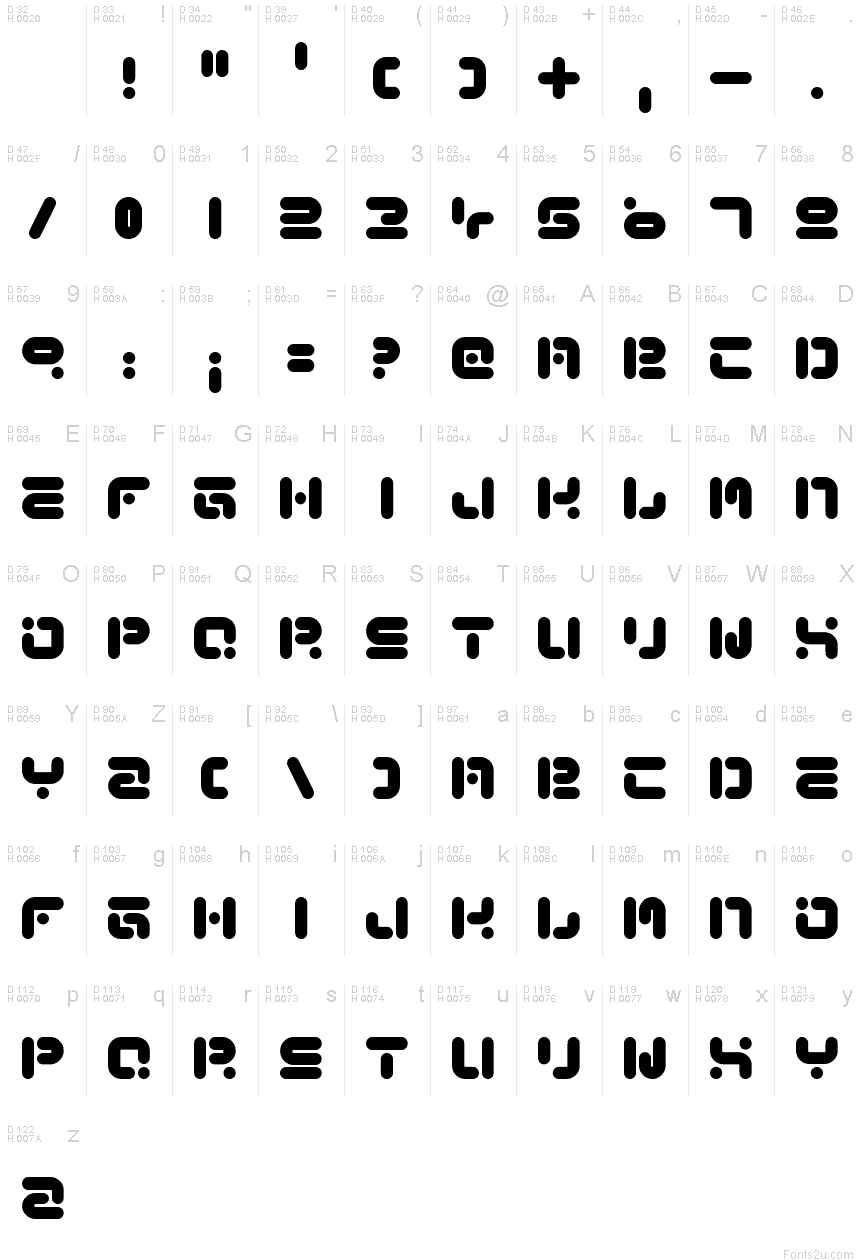
Funky Knut Sober od Mr. Mieps to darmowy, futurystyczny krój displayowy o błyszczącej, gumowej energii. Jego masywne, zaokrąglone elementy i ciasny rytm pionowy przypominają rzędy neonów, które płynnie zakrzywiają się na każdym rogu, zachowując jednocześnie stabilną, modułową siatkę. Efektem są wyraziste, czytelne napisy, które sprawiają wrażenie zabawnych i nieco nieziemskich, niczym szyldy z retro-futurystycznego salonu gier.
Wykorzystaj Funky Knut Sober w nagłówkach na plakatach science-fiction, ulotkach klubowych, okładkach muzyki elektronicznej, brandingu wydarzeń technologicznych, nakładkach do gier, naklejkach oraz wyrazistych grafikach do mediów społecznościowych. Ten darmowy font najlepiej sprawdza się w dużych rozmiarach, gdzie jego łukowate kształty i punktowe wnętrza liter naprawdę przyciągają wzrok. W przypadku mniejszych tekstów, zestaw go z czystym krojem bezszeryfowym o geometrycznej budowie, aby zachować ostrość i czytelność projektu.